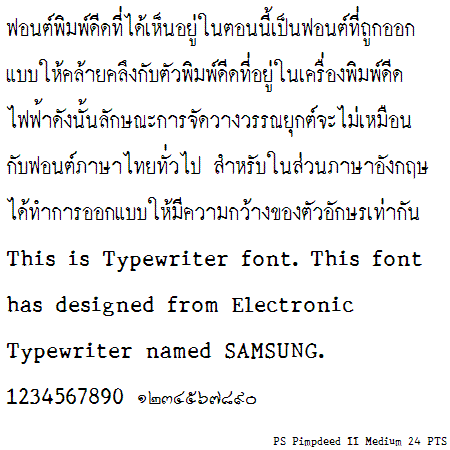
ฟอนต์ตัวนี้ทำไว้นานแล้ว เป็นฟอนต์ตัวแรกๆ ที่ผมทำ ได้จัดทำให้เหมือนกับเครื่องพิมพ์ดีดไฟฟ้ามากที่สุด ดังนั้นหากจะนำไปเปรียบเทียบกับเครื่องพิมพ์ดีดธรรมดาจะเห็นว่าความคมชัด ต่างกัน ในฟอนต์ตระกูลนี้ จะมีหลายลักษณะ ก็ขึ้นอยู่กับว่าเอาไปทำอะไร ใช้ได้กับโปรแกรม ออฟฟิศอย่างเดียวครับ กำลังพัฒนา OT อยู่ครับ คงจะมีเวอร์ชั่นใหม่เร็วๆ นี้
PS Pimpdeed Family